首位进入国际平面设计联盟(AGI)的华人设计师、清华大学教授余秉楠近日在京逝世,享年87岁,为《辞海》设计字体的他曾经影响过一代又一代设计人。
北京 | 中国首位AGI成员、清华大学教授余秉楠
87岁辞世,影响过一代又一代设计人
余秉楠(1933-2020)清华大学美术学院9月25日发布讣告:杰出的艺术设计教育家、设计家,中共党员、离休干部,清华大学美术学院视觉传达设计系教授余秉楠先生,因病医治无效,于2020年9月24日在北京逝世,享年87岁。1992年,余秉楠是首位进入国际平面设计联盟(AGI)的华人设计师。他在书籍设计与字体设计都有非凡的成就,将网格系统与西文设计带到了中国。
余秉楠1933年出生于上海,1956年毕业于鲁迅美术学院,然后经过中国文化部的考核,余秉楠被选派到民主德国学习。余秉楠是新中国第一代选派的留学生。学成归国之后,创作了许多优秀的作品,出版了多本设计书籍,也成为清华大学、中央美术学院等多所高校的客座教授,影响了一代又一代的设计人。
“友谊体”是余秉楠的成名之作,也是对中国十分有历史意义的一套字体。留学期间,余秉楠接到老师给的第一个创作任务——一副适合用于多种排版、在中国使用的字体。
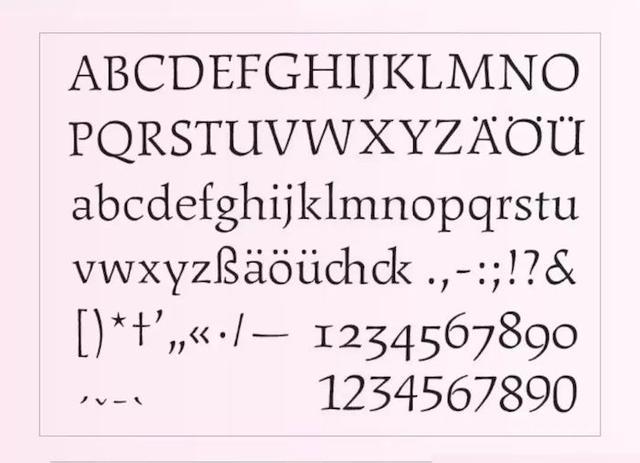
友谊体作为中国人设计的第一套正文拉丁字母,友谊体在历年内获得了谷滕堡终生成就奖(首位亚洲获奖者)、“当代最佳印刷字体”奖、德国文化部长奖、东京艺术指导俱乐部(TDC)奖等多个奖项。
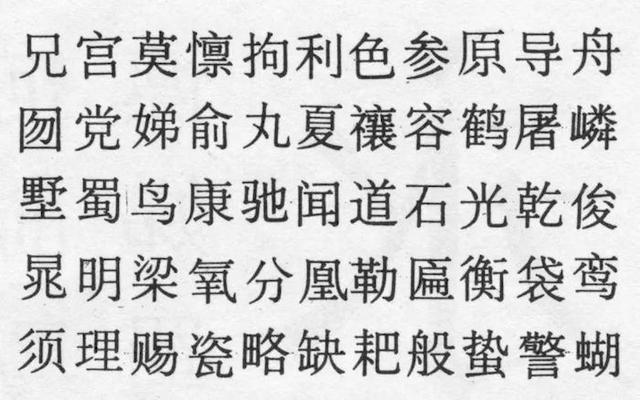
《辞海》的字体,宋一体、黑一体、宋二体、黑二体1962年,余秉楠以优异的成绩从莱比锡毕业,谢绝了导师的挽留后便回国了。回国之后,余秉楠加入了上海印刷技术研究所,参与了为《辞海》设计的“宋一”、“黑一”和为《毛选》设计的“宋二”、“黑二”。1963年,余秉楠为《辞海》专门设计了一款拉丁文字体,名为“辞海细体”,该字体是新中国生产的第一套拉丁字母印刷活字。1987年,为了甩掉以往宋体的“角”,摆脱机械感,余秉楠通过马克笔的反复书写试验,最终创作完成了一款名为“圆宋”的印刷字体。(文/畹町)亚洲 | 佳士得亚洲区前总裁魏蔚
郭利伟9月26日,艺术家郭利伟的个展“心游大荒”在上海BAC竹园艺术中心开幕。展览集中展示了郭利伟三个作品系列——《游园》、《山行》和《石孕》。郭利伟的作品包含东方美学的特质,他将中国书法的线性技法运用于绘画创作中,取代了传统西画对光影和透视关系的强调。另一方面,他熟悉西方创作媒介的属性,其浓烈的颜色和肌理质感为中式景致带来了历史感。
郭利伟“心游大荒”个展作品此次展览借用了清代黄钺所著《二十四画品》其中的一品“沉雄”作为策展线索,即“目极万里,心游大荒。魄力破地,天为之昂”。用古代文人的美学观来形容郭利伟的创作颇为契合,大气而不张扬,洒脱而不混吝,在东方的含蓄之中隐含着力量。郭利伟1974年出生于河南郑州,1995年毕业于上海交通大学工业设计系,美学观的背后反映了个体的自身语境和道德观。成长于北方黄河流域的画家,骨子里带着中原文化的烙印——粗旷、热烈、厚重、沉稳、谦逊。因而,他刻画的园林、庭院、石山等也呈现着拙朴气质,他对写意的追求也是内心的写照。(文/畹町)
上海|工艺美术大师季益顺
呈现当代紫砂艺术的传承与探索
在从艺四十年之际, 六十岁的中国工艺美术大师季益顺9月27日于上海中心大厦宝库文化中心举办了“金玉琅琅·云间抟砂”——季益顺师徒紫砂作品暨“福禄寿·玉金砂”展,展出了季益顺及其主要弟子的作品,呈现了当代紫砂艺术的传承与探索。
季益顺季益顺 1960年生于陶艺之家,后随紫砂名家高丽君、王小龙学艺。在恩师的言传身教下,对紫砂艺术有着深刻理解的他,练就了精湛、娴熟而全面的手工制壶技艺,年轻时即在紫砂壶艺界崭露头角。他在继承千年紫砂的文化传统的同时,不墨守成规,将高雅的紫砂艺术与“日用”功能有机结合起来,在造型与装饰上都有重大的突破和创新。他将壶艺造型与中国书画、雕塑完美相融,“画在壶上、壶在画中”,开创并形成了具有“诗情画意”特色的“季益顺紫砂艺术流派”。他的《江南水乡一景》五件组壶获第八届全国陶瓷创新设计评比金奖。